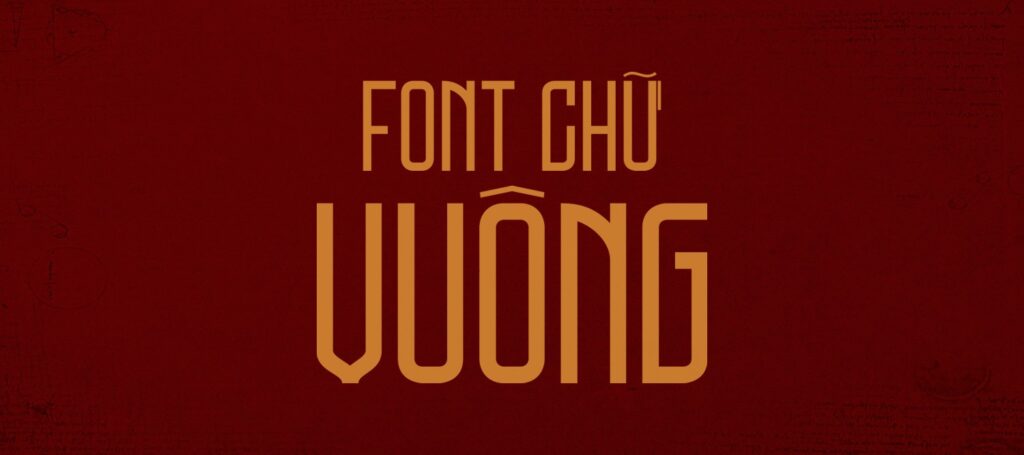
Trong ngôn ngữ thiết kế hiện đại, các dòng font chữ vuông luôn mang lại cảm giác ổn định, mạnh mẽ và đầy tính kỷ luật. Với cấu trúc hình học dứt khoát, phông chữ này đặc biệt phù hợp để trình bày các tiêu đề hồ sơ kỹ thuật, bảng hiệu nhà xưởng hay các bộ nhận diện thương hiệu ngành xây dựng.
Đặc điểm thẩm mỹ nổi bật của dòng font chữ vuông
Nét lôi cuốn đặc trưng của phông chữ vuông nằm ở sự tối giản và khả năng tận dụng không gian hiển thị hiệu quả. Khác với các dòng phông chữ uốn lượn, font chữ dạng khối tập trung vào các đường thẳng và góc cạnh, tạo nên vẻ ngoài vững chãi như những khối module trong nhà lắp ghép. Phiên bản font chữ vuông Việt hóa đã được tinh chỉnh hệ thống dấu thanh sao cho không làm phá vỡ sự cân đối của khung chữ, đảm bảo văn bản luôn giữ được sự chỉn chu và dễ nhận diện.
Bên cạnh phong cách góc cạnh truyền thống, xu hướng font chữ vuông bo góc đang ngày càng được ưa chuộng nhờ sự giao thoa giữa sức mạnh và tính thân thiện. Các đường bo góc nhẹ nhàng giúp làm dịu đi sự thô cứng của các khối chữ lớn, mang lại vẻ đẹp hiện đại và tinh tế. Đây là phương án hiệu quả để truyền tải các thông điệp về sự đổi mới, công nghệ và gu thẩm mỹ đương đại cho mọi dự án sáng tạo từ phối cảnh kiến trúc đến ấn phẩm truyền thông.
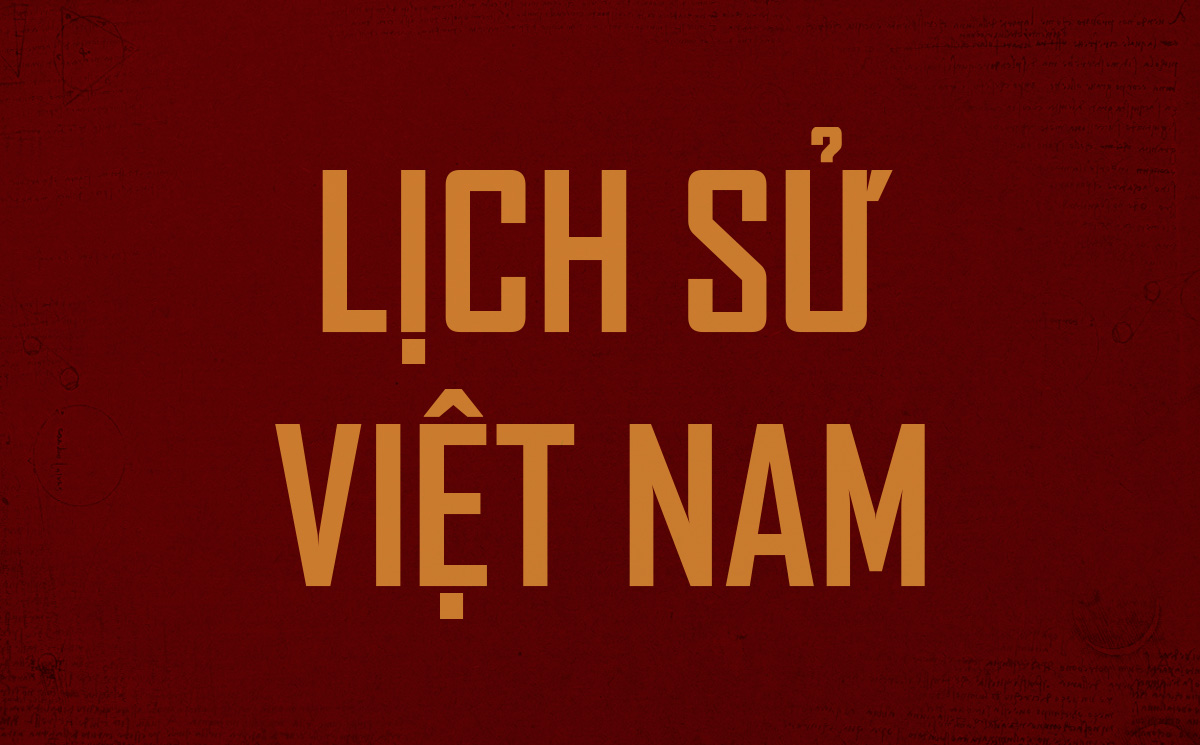
Hồ sơ tài nguyên bao gồm đa dạng các biến thể từ phông chữ kỹ thuật đến font chữ triện vuông mang âm hưởng văn hóa Á Đông. Dưới đây là thông số chi tiết để bạn tham khảo trước khi cài đặt.
| Phân loại phong cách | Geometric / Square / Decorative |
| Nhóm phông tiêu biểu | Square Sans, Font chữ triện, Font vuông bo góc |
| Mục đích phù hợp | Tiêu đề hồ sơ, Logo, Bảng hiệu nhà xưởng |
Tư vấn lựa chọn: Nếu dự án của bạn hướng đến sự hiện đại và công nghệ, hãy chọn các dòng font vuông Việt hóa tối giản. Trong khi đó, việc download font chữ triện vuông sẽ là gợi ý phù hợp cho các không gian mang tính hoài cổ, trang trọng hoặc các biển tên nhà vườn, homestay phong cách truyền thống.
03 Ứng dụng phông chữ vuông vào thực tế xây dựng
Nhờ diện mạo vững chãi và độ rõ nét cao, bộ phông chữ này mang lại giá trị thực tế lớn trong khâu quảng bá và hoàn thiện công trình:
- Hệ thống nhận diện cho nhà xưởng & văn phòng: Những nét chữ vuông vức rất ăn ý khi gia công cắt chữ nổi inox hoặc alu. Font chữ này giúp biển tên công ty toát lên vẻ chuyên nghiệp, tạo niềm tin về quy mô và chất lượng dự án đối với đối tác.
- Ghi chú thông số kỹ thuật chính: Sử dụng font vuông Việt hóa cho các số hiệu quan trọng trên bản vẽ AutoCAD giúp thông tin trở nên tách bạch, hỗ trợ đội ngũ giám sát thi công tra cứu dữ liệu nhanh chóng và chính xác.
- Trang trí không gian nội thất Industrial: Bạn có thể dùng font chữ vuông để in decal dán kính hoặc bảng nội quy văn phòng container, tạo nên một môi trường làm việc ngăn nắp, đồng bộ với phong cách kiến trúc công nghiệp.
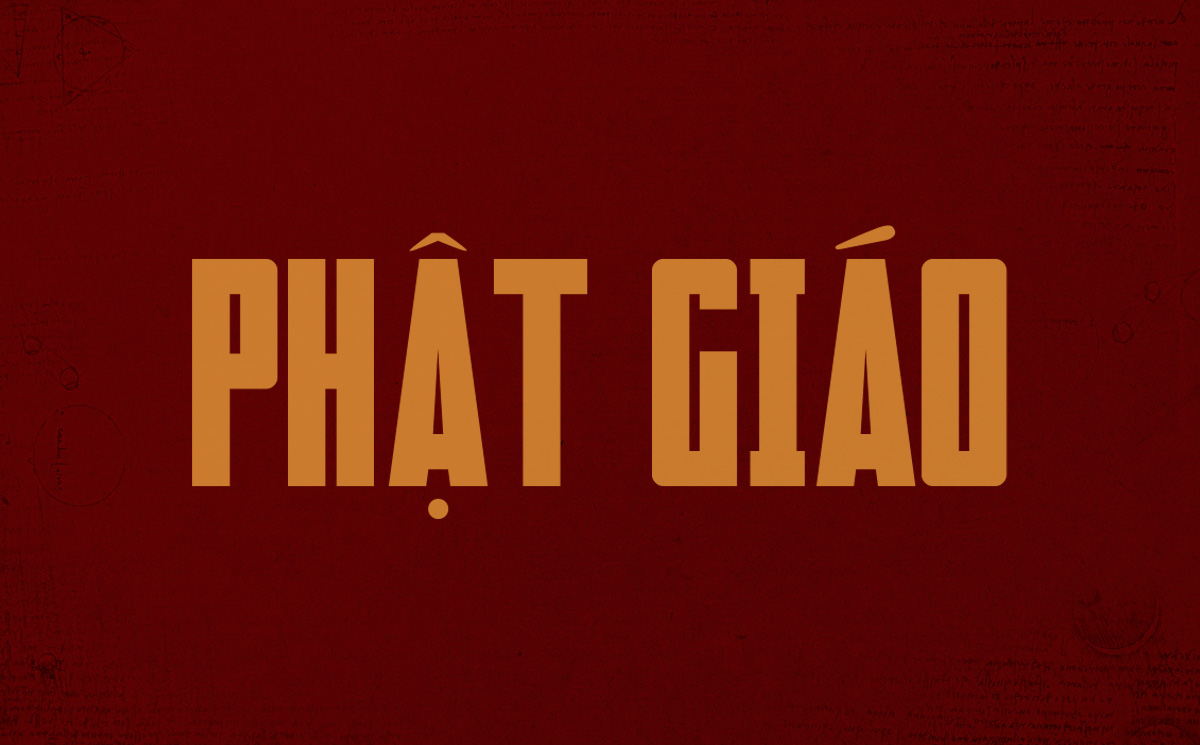
03 Lưu ý để bố cục bản thiết kế với font chữ vuông chỉn chu
Để khai thác hiệu quả vẻ đẹp của dòng font đặc thù này mà không làm rối mắt người xem, người thiết kế nên lưu tâm một số kinh nghiệm kỹ thuật sau:
- Kiểm soát khoảng cách dòng và chữ: Do cấu trúc chữ vuông thường rộng ngang và chiếm diện tích, bạn nên nới rộng khoảng cách giữa các dòng để văn bản thông thoáng hơn, tránh cảm giác bí bách khi trình bày trên khổ giấy nhỏ.
- Hạn chế dùng cho đoạn văn bản dài: Chỉ nên sử dụng font chữ vuông cho các tiêu đề chính hoặc các cụm từ nhấn mạnh. Việc lạm dụng cho các đoạn thuyết minh dài sẽ gây mỏi mắt và làm giảm hiệu quả truyền tải thông tin.
- Phối hợp cùng font không chân mảnh: Để tạo ra sự cân bằng, hãy phối hợp font vuông cùng các phông chữ Sans-serif mảnh và thoáng cho phần nội dung phụ. Sự tương phản này giúp bản vẽ trở nên chuyên nghiệp và hiện đại hơn.